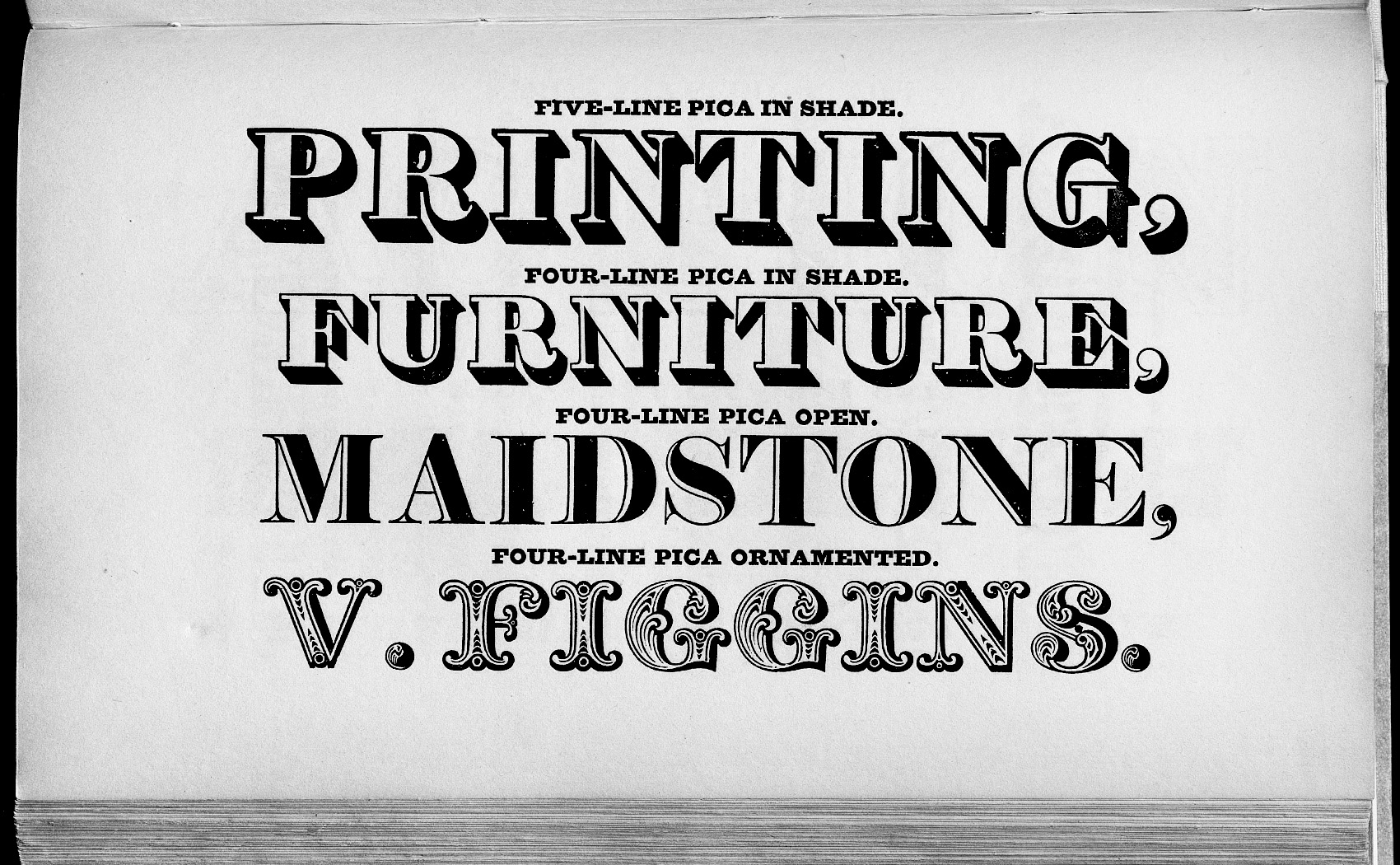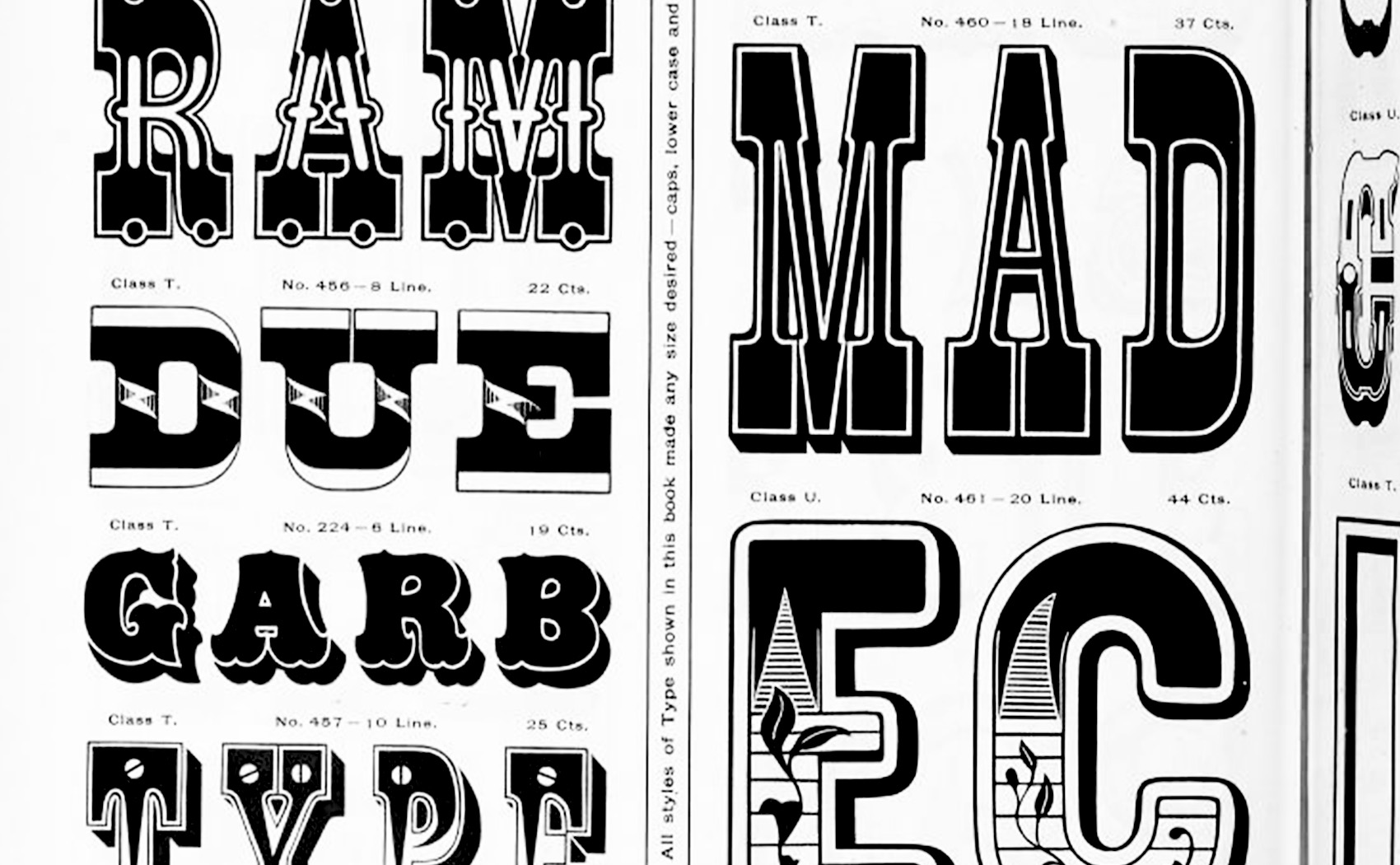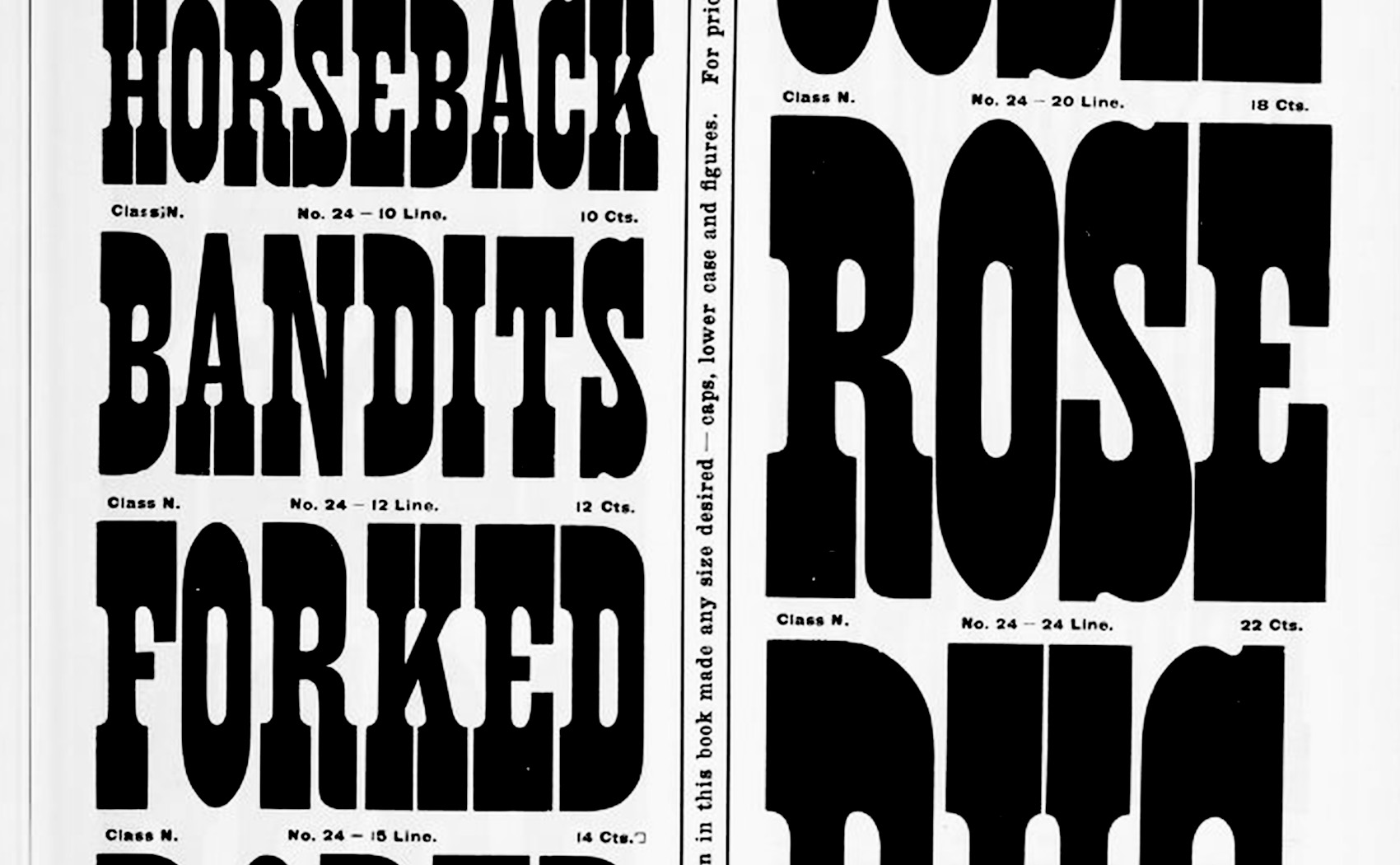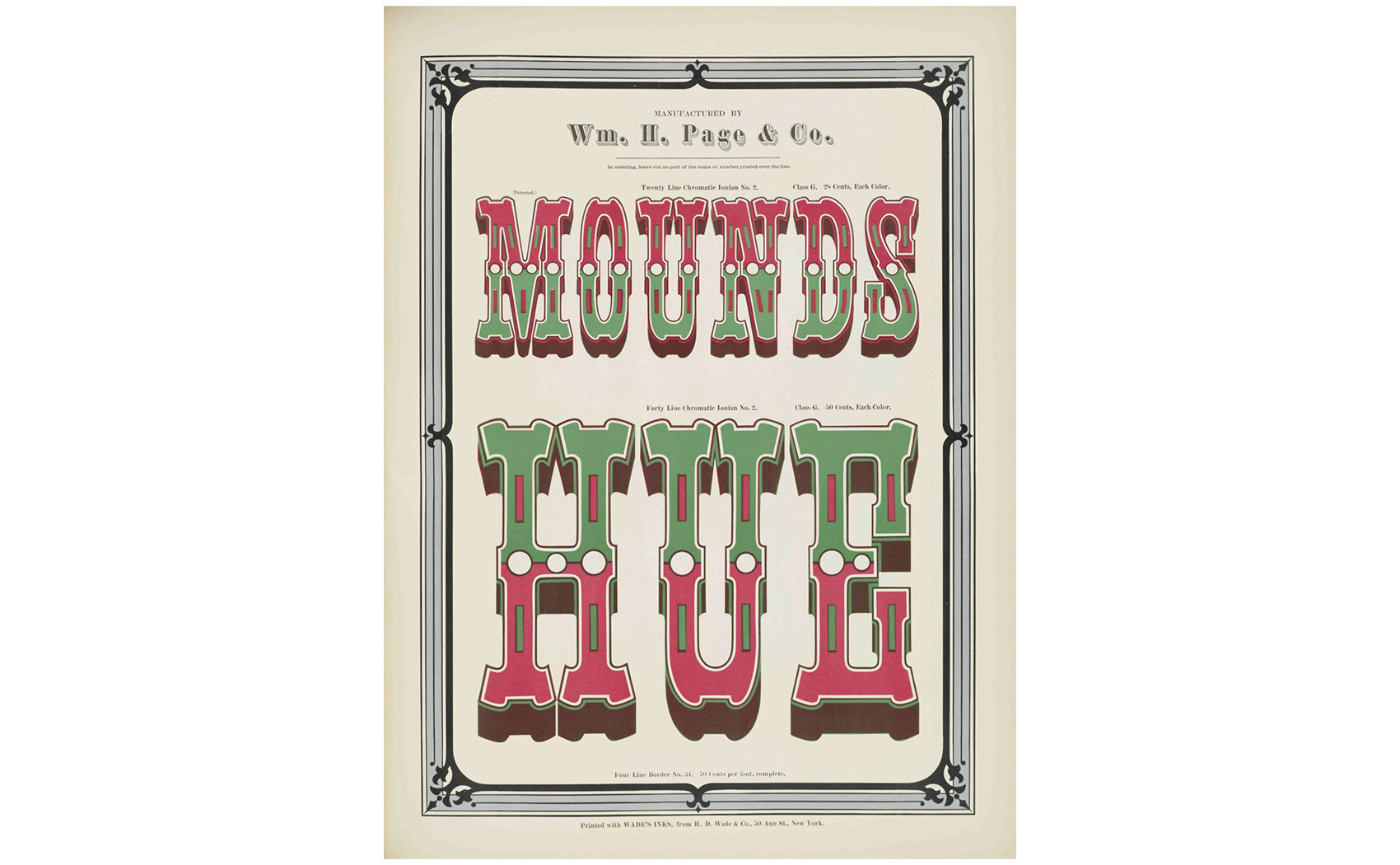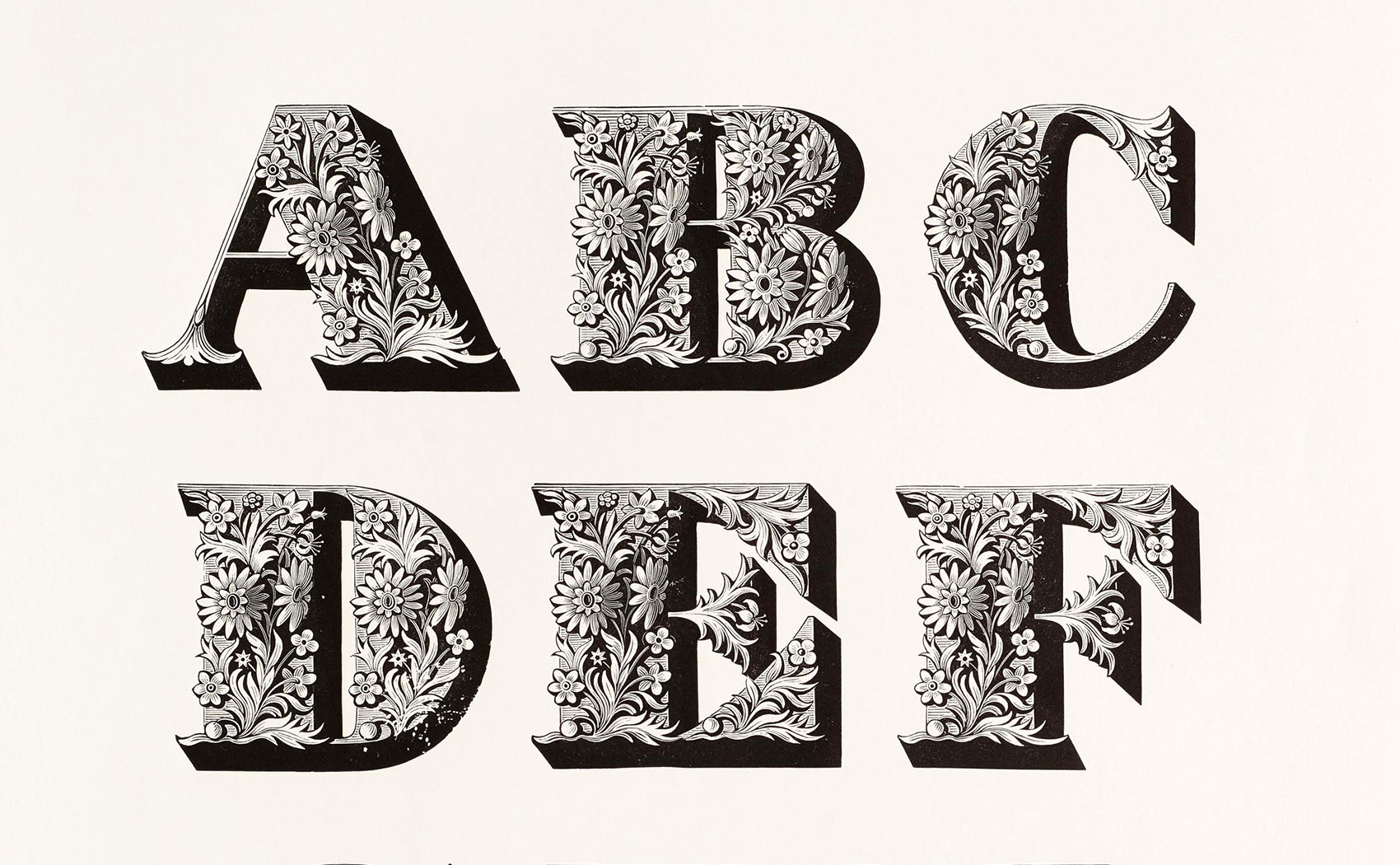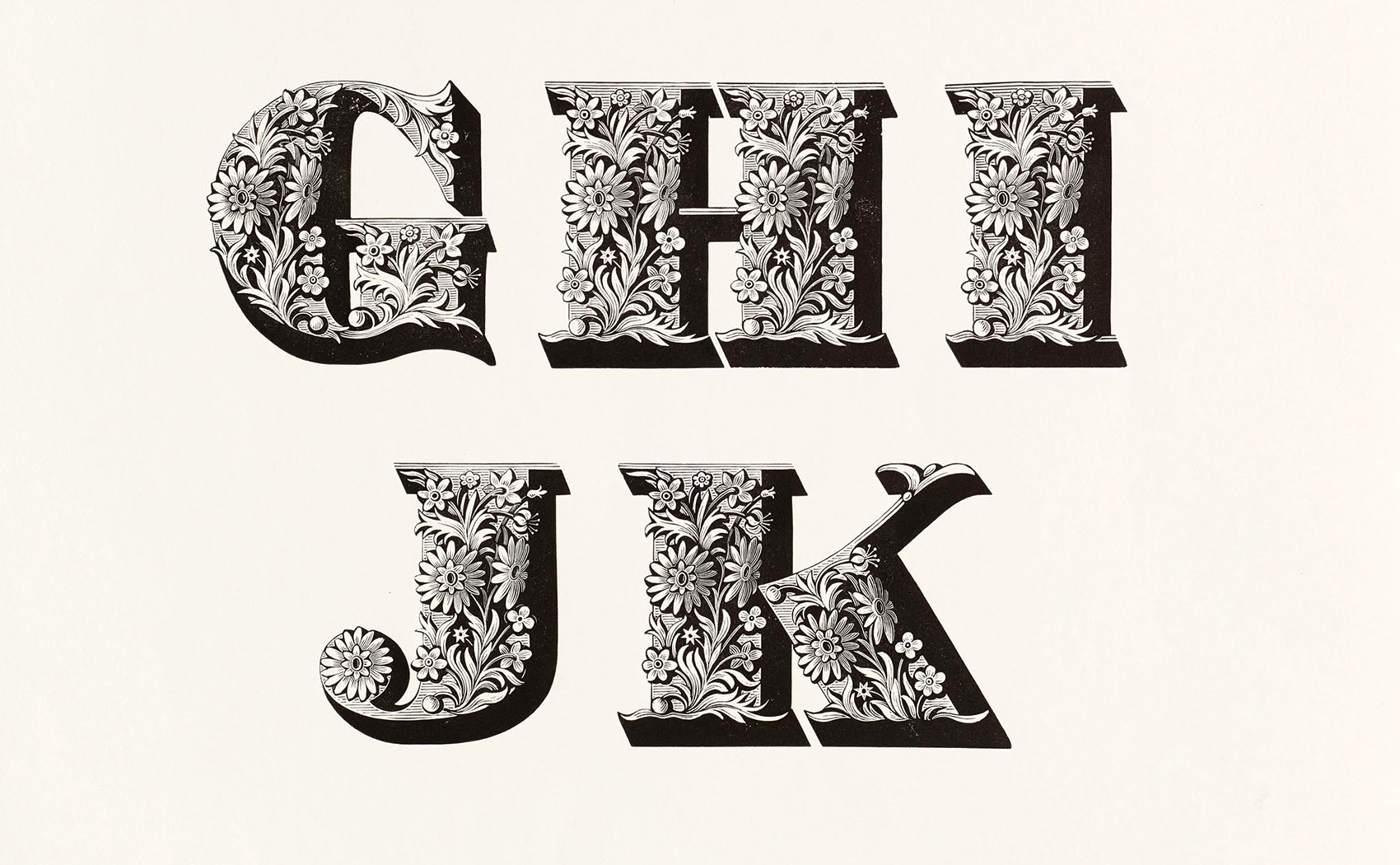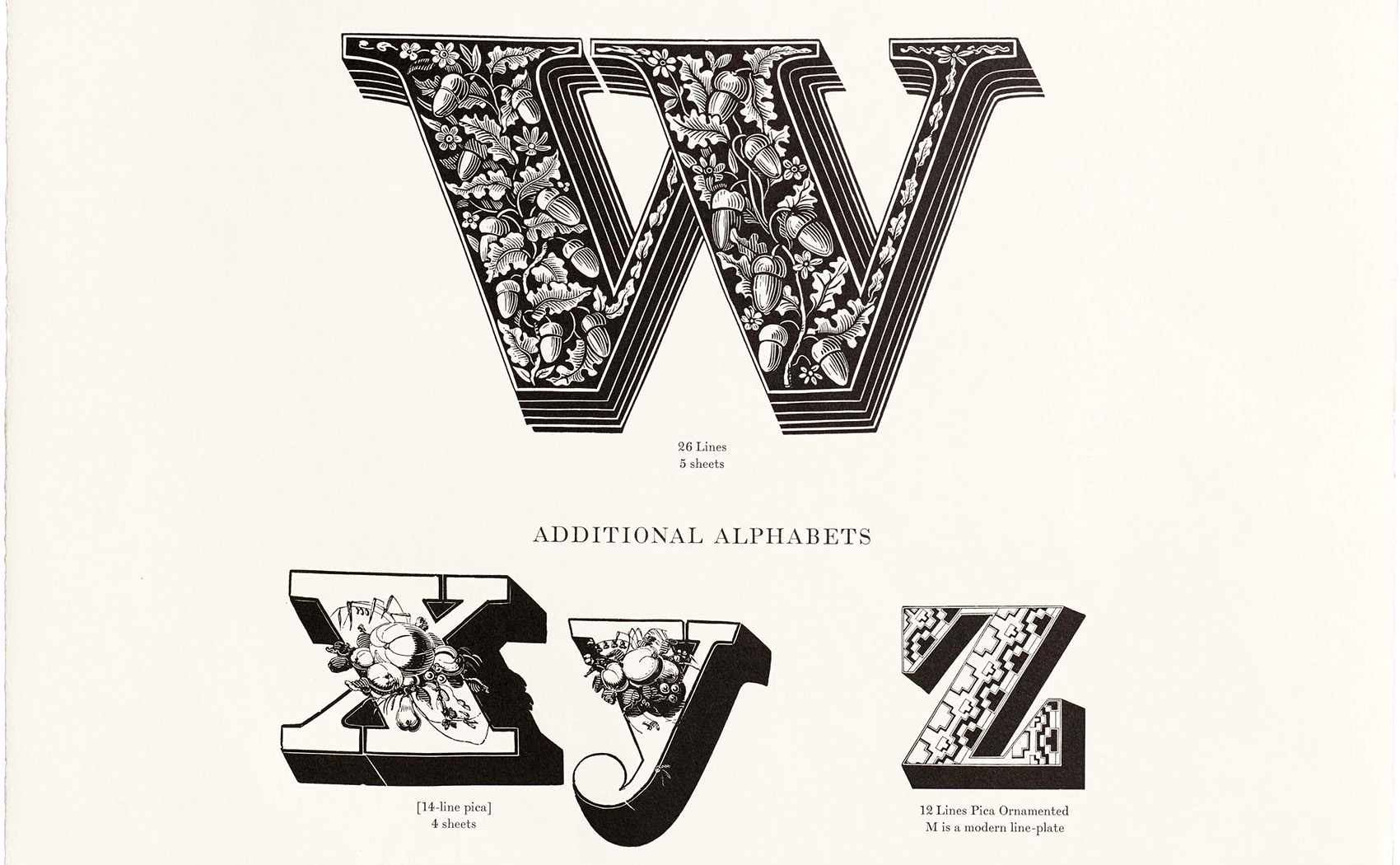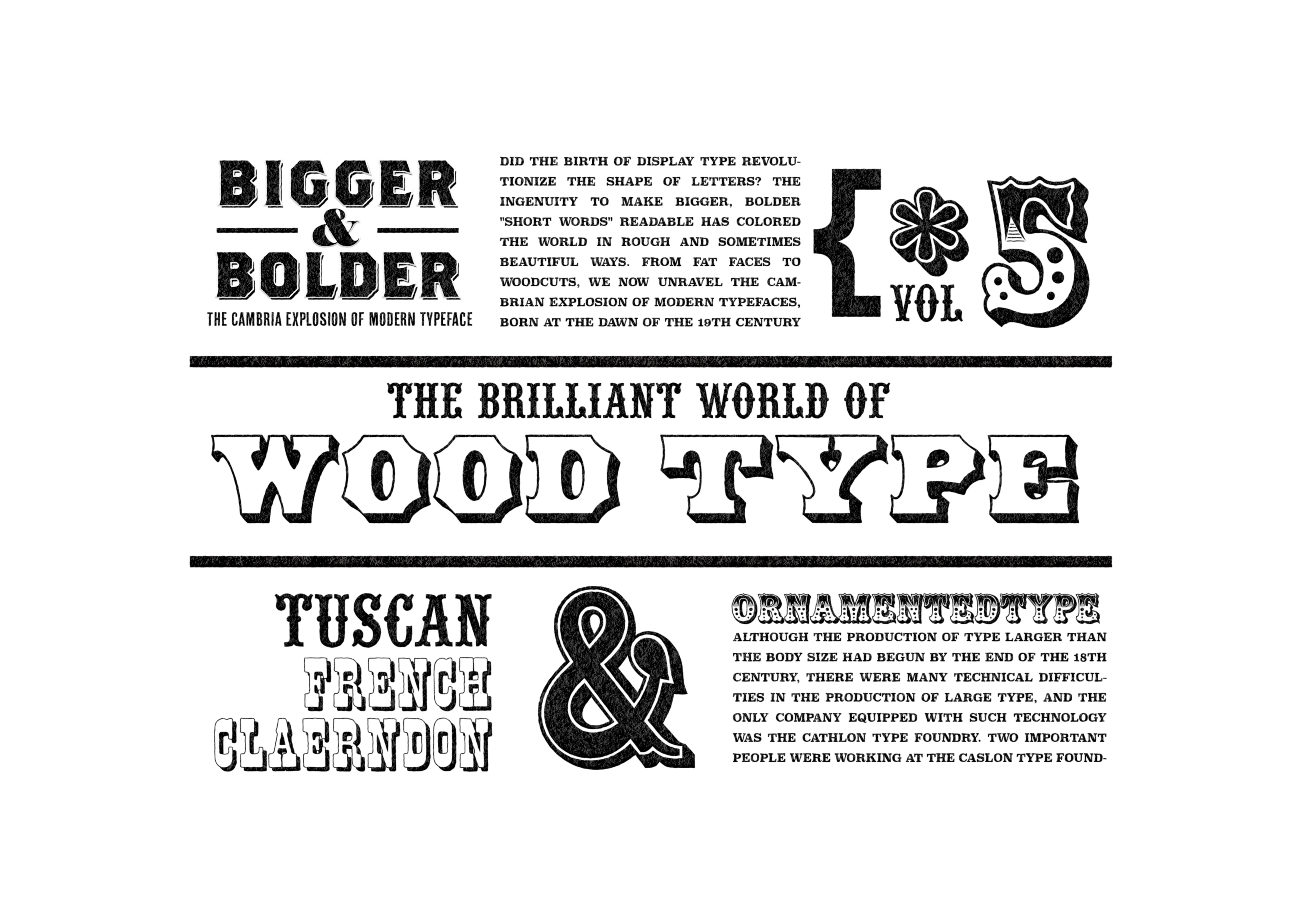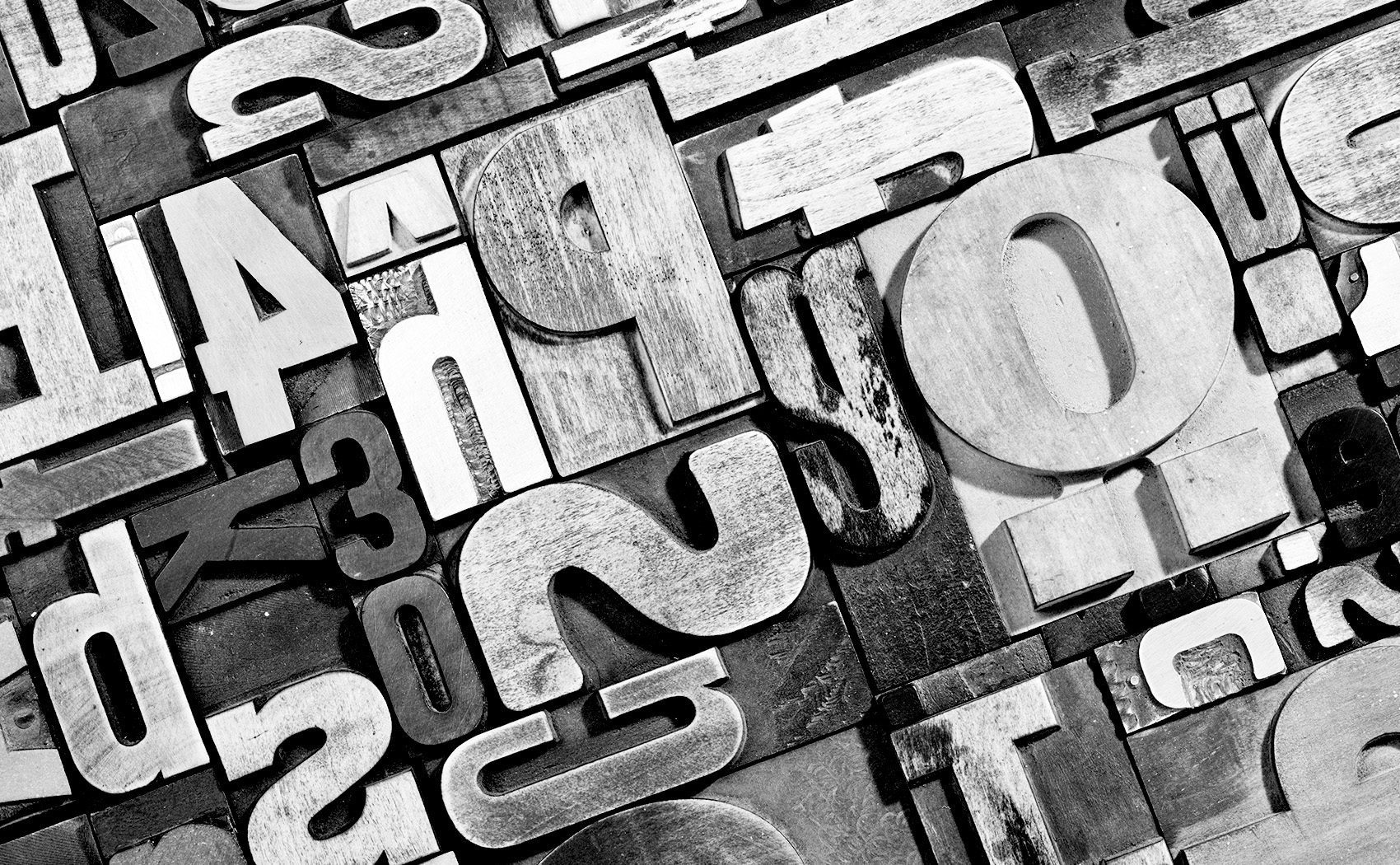
BIGGER & BOLDER
The Cambria Explosion of Modern Typeface
—Vol.05 ウッドタイプの華麗なる世界—
THE BRILLIANT WORLD OF WOODTYPE
ウッドタイプの華麗なる世界
「短い言葉」を読ませるためにディスプレイタイプがより太くより単純化して「黒み」を追求するファットフェイスやスラブセリフの方向性へ進むのと平行して、活字の形にさらに視覚的な要素を追加して文字をいかに「目立たせる」かを追求する「装飾」の可能性を探る方向性が存在していました。 もともと文字を装飾することは、古くは聖書の写本のイニシャルといわれる装飾頭文字のカリグラフィーにおけるテクニックや、近代においてもレタリングやサインペインティングなどで育まれてきた文化があり、それがディスプレイタイプの黎明期に活字に取り入れられることとなりました。おりしも産業革命後のヴィクトリア朝時代は、バロックやロココなどの前時代の貴族的な装飾が、機械化による大量生産技術の開発に伴って安価に行き渡る大衆化がおきていて、デザイン史の中でも装飾の特異点と考えられています。そんな猫も杓子も装飾マシマシなモダンデザイン前夜に起きた、活字の装飾について少しのぞいてみたいと思います。
In parallel with the trend toward fat faces and slab serifs, which pursue “blackness” by making display type thicker and simpler in order to make “short words” readable, there was a trend toward exploring the possibilities of “decoration,” which seeks how to make letters “stand out” by adding more visual elements to the typeface form. Originally, the use of decorative letterforms was a technique in calligraphy, where initials in biblical manuscripts were used to decorate letters, and in modern times, lettering and sign painting have been used to decorate letters. This culture was incorporated into type at the dawn of display type.In the Victorian era after the Industrial Revolution, the aristocratic decorations of the Baroque and Rococo periods were being popularized at low cost with the development of mass production technology through mechanization, and this period is considered a singular point in the history of design. Let us take a look at the decoration of type on the eve of the modern design era, when all the cats and dogs were decorated.
ウッドタイプの誕生The Birth of Wood Type
19世紀までヨーロッパでは活字を作るためには金属鋳造が基本でした。金属活字は一度元となる父型(パンチ)に文字の形を彫刻し、それを母型(マトリクス)に打ち付けて鋳型をつくります。鋳型をつかって鋳造によって複製をしてゆくことで大量に同一の文字を制作することが可能です。それに対して、木製の活字は手作業によって一つづつ複製を強いられるため量産ができず実際的ではないと考えられてきました。時は産業革命の真っ只中、動力を生かした発明に頭をひねる人々がしのぎを削る中、1827年にダリウス・ウェルズが木工機械である「ルータ」を発明したことで状況は一変することになります。ルータは動力を得て木を削ることや磨くことが可能で、この機械化により木製の活字を制作する時間が大幅に短縮し大量生産が可能となりました。そして、1834年に「パントグラフ」が発明されルータとの組み合わせにより手元の作業を正確に拡大複製することが可能となったことで、ウッドブロックをつかった「大きな活字」を制作する条件が整います。ファットフェイスが切り開いたポスター向けのディスプレイタイプの「大きな活字」の需要は右肩上がりに増えているなか、大量生産が可能となった木製の活字は金属活字に対して10分の1程度の価格で提供することが可能でウッドタイプがディスプレイタイプのマーケットへと進出します。さらにダビングやプロトタイピングなど、木製から金属への複製技術の発展もウッドタイプによる装飾などディスプレイタイプのデザインを豊富なものにしてゆきました。
Until the 19th century, metal casting was the basic method of making type in Europe. The metal type was made by engraving the letterforms on a punch, which was then struck into a matrix to make a mold. By using the mold to make reproductions through casting, it is possible to produce identical letters in large quantities. Wooden type, on the other hand, was considered impractical because it could not be mass-produced because it had to be reproduced one by one by hand.In the midst of the Industrial Revolution, when many people were busy trying to come up with new ideas using power, the situation changed when Darius Wells invented the “router,” a woodworking machine, in 1827. The router was powered to sharpen and polish wood, and this mechanization greatly shortened the time required to produce wooden type and enabled mass production. The invention of the “pantograph” in 1834, combined with the router, made it possible to accurately enlarge and reproduce the work at hand, thus creating the conditions for the production of “large type” using wood blocks. The demand for large display type for posters, which Fat Face had pioneered, was steadily increasing, and wood type, which could now be mass-produced at one-tenth the price of metal type, entered the display type market. Wood type entered the display type market. The development of wood-to-metal reproduction techniques, such as dubbing and prototyping, also contributed to the proliferation of display type designs, such as wood type decorations.
ウッドタイプのデザインWoodtype design
産業革命を果たした19世紀のロンドンから、20世紀の中心になる新天地アメリカへと産業や文化が大きく動くとともに、文化の中心をささえる文字もまた求めに応じてカタチを変えてきました。特にウッドタイプの需要が急増した1860年から1890年代のアメリカは西部開拓時代にあたり、開拓の歴史とともにアメリカの文化の根底にウッドタイプが深く刻みこまれてゆくこととなります。ウッドタイプをタイプフェイスデザインの面からみた時、代表的なデザインスタイルには「トスカン」と「フレンチクラレンドン」を挙げることができます。トスカンもクラレンドンもデザイン自体はもともと19世紀のロンドンからやってきました。そう、フィギンズやファンストリートのデザインです。それらが、アメリカで独自の発展を遂げ、いまでは「トスカン・クラレンドン=ウッドタイプ=古き良きアメリカ」のような連想が成立するほど、アメリカ文化と密接なデザインとなっています。ウェスタン映画やベースボールチームに至るまでアメリカ文化には必ずといっていいほどウッドタイプ由来のエレメントが用いられています。
As industry and culture moved from London in the 19th century, the center of the Industrial Revolution, to the United States, the new center of the 20th century, the letters that supported the center of culture also changed form to meet the needs of the times.The 1860s to 1890s, when demand for wood type rapidly increased, was the era of the western frontier, and wood type was deeply engraved in the foundation of American culture as well as the history of the frontier.From the standpoint of type face design, Tuscan and French Clarendon are representative of wood type. Both Tuscan and Clarendon designs themselves originally came from 19th century London. Yes, they are Figgins and Fann Street designs. They have developed in their own way in the United States and are now so closely connected to American culture that the association “Toscan/Clarendon = wood type = good old America” is now established. Elements of the wood type are used in American culture, from western movies to baseball teams.
トスカンTUSCAN
トスカンは特徴的な装飾されたセリフやエレメントを持つものを分類する用語として用いられています。シェイプの特徴では、セリフが二つや三つに枝分かれしたものや、ステムなどの直線部分を絞るような曲線となっていたり、ベースラインとアセンダーラインの中央あたりに装飾的な特徴を持つものをさします。ウッドタイプで好んで用いられたことからウッドタイプと同義的に分類されている場合もあります。ヴィンセント・フィギンズの1801/1815年のカタログに掲載された、FOUR LINE PICA ORNAMENTEDが欧文活字での最初のトスカンであり、ローマンをベースにした文字形で、過度に曲線的で装飾的なセリフと、文字内部へ彫刻のような装飾を施した特徴的なデザインです。
Tuscan is a term used to classify those with distinctive decorated serifs or elements. In terms of shape characteristics, it refers to serifs with two or three branches, curved lines that narrow the stem and other straight parts, and decorative features around the center of the base line and ascender line. Since it is often used in wood types, it is sometimes classified synonymously with wood typesFOUR LINE PICA ORNAMENTED from Vincent Figgins’ 1801/1815 catalog is an early Toscan in European type, a Roman-based letterform with overly curved and decorative serifs and a distinctive design with engraved ornamentation inside the letters. .
アメリカとウッドタイプWood type in US
ウッドタイプはヨーロッパから海を渡った新天地アメリカでさらに独自の発展を遂げてゆくこととります。アメリカ国内で最初にウッドタイプとしてトスカンが登場したのが、Edwin Allen のものが1838年のEdwin Allen 「First Premium Wood types , cut by machinely」に掲載されています。19世紀のアメリカでは機械化した木工によりウッドタイプのファウンダリが成功をおさめ、さまざまなウッドタイプが生まれました。
The wood type was to further develop in its own unique way in the United States, a new country that had crossed the ocean from Europe.The first wood type Tuscan to appear in the U.S. was made by Edwin Allen in 1838 in his “First Premium Wood types , cut by machinely. The success of the wood type foundry led to the creation of a wide variety of wood types.
アンティークトスカンANTIQUE TUSCAN
1850年から1860年にかけてつくられた、スラブセリフを原型に縦線を絞るように曲線でカットしたアンティークトスカンと呼ばれるデザイン。
The design called an antique toscan, was made between 1850 and 1860 and is based on a slab serif, cut with a curved line that narrows the vertical line.
フレンチクレランドンFRENCH CLARENDON
フレンチクラレンドンは、縦線と横線の太さのコントラストが典型的なものとは逆にになったリバースコントラストが特徴のデザイン。同時代にはリーバースコントラストのイタリアンと呼ばれるタイプデザインがあり、スラブセリフなどとともに太いセリフに特徴を持たせることでユニークさを強調している。19世紀のアメリカで好んで用いられたことで、現代でも西部開拓時代を演出する際に、指名手配のビラのWANTEDや、西部劇やテーマパークなどの看板などでしばしばつかわれています。
French Clarendon is a design characterized by reverse contrast, in which the contrast between the thickness of the vertical and horizontal lines is reversed from the typical one. The type design of the same period, called Italian with leavers contrast, emphasizes the uniqueness of the thick serifs by making them distinctive, along with slab serifs, etc. A favorite in 19th century America, it is still used today in Westerns, such as WANTED on wanted flyers, and on signs in Westerns and theme parks.
ウッドタイプの装飾Wood Type Decoration
文字自体のフォームのデザインよりも、装飾性という部分でウッドタイプは鋳造活字では不可能だった細やかな装飾を可能にしました。加工の容易な木版はイラストレーションに向いており、もともと凸版印刷において、金属活字と木版のイラストレーションという組み合わせで行われていたものが、ウッドタイプの登場で、文字にイラストレーティブな装飾を施したものや木版画の手法を持ち込んだ表現が数多く登場しました。その中でも装飾の完成度の高かった、ルイ・ジョン・プーシェ Louis John Pouchée のアルファベットと、多色印刷が可能なWilliam Hamilton Pageのクロマティックウッドタイプを紹介します。
More than the design of the form of the letter itself, wood type enables detailed decoration that was not possible with cast type. Woodblock, which is easy to process, is suitable for illustration. Originally, the combination of metal type and woodblock illustration was used in letterpress printing, but with the advent of woodtype, many illustrative decorations were added to the letters and woodcut techniques were brought into the process. The wood type was a combination of type and woodblock illustration.This section introduces Louis John Pouchée’s alphabets, which were highly decorated, and William Hamilton Page’s chromatic wood types, which could be printed in multiple colors.
W・HページのクロマティックWillam Hamilton Page
19世紀のアメリカでウッドタイプのデザインの主要人物でクロマティックウッドタイプを開発して大成功しました。クロマティティックタイプとは多色刷りを可能にするウッドタイプで、重ね刷りするために色数にセパレートしたデザインをもつ活字です。
Willam Hamilton Page was a major figure in 19th-century American wood type design and a highly successful developer of chromatic wood type. Chromatic type is a wood type that allows multi-color printing and has a design that separates the number of colors for overprinting.
ルイ・ジョン・プーシェの装飾Louis John Pouchée
もっとも美しいとされているウッドタイプとして名高いルイ・ジョン・プーシェ Louis John Pouchée のアルファベット。1820年代に手彫りされた活字としてはもっとも豪華な装飾が施されたものです。レターフォームはソーンのファットフェイスをベースにしていますが、技巧に富んだ豪華な装飾が施されており目を見張るものがあります。写真はロンドンのセント・ブライド・プリンティング・ライブラリー所蔵のもの。
Louis John Pouchée alphabet, considered one of the most beautiful wood types, is the most ornately decorated hand-engraved type of the 1820s. The letterforms are based on the Thorne fat face, but are spectacularly decorated with skillful and lavish ornamentation. The photograph is from the collection of the St. Bride’s Printing Library, London.
ウッドタイプの現在Woodtype today
現在では、活版印刷と同様に大規模に使われることは無くなりましたが、独自のカスレによる温かみや豊富な装飾は近年の再評価も入り今も人々を惹きつけています。木製で相当数が製作されていたため現存しているものも多く、アメリカ国内ではアンティークのインテリア雑貨などを扱う店で見かけることもあります。さまざまなフォントがデジタイズされており、ウッドタイプのタイプフェイスデザインをデジタルフォントで利用することができます。とくに2012年に設立されたHWT(Hamilton WoodType Collection )ではウッドタイプの特徴的でクラシックなものが数多くリバイバル・デジタイズされています。
Today, as with letterpress, it is no longer used on a large scale, but the warmth of its unique cusps and abundant decoration have been reevaluated in recent years and still attract people today. Many of them are still in existence, and can be found in antique stores selling interior goods in the United States.Various fonts have been digitized, and wood typeface designs can be used in digital fonts. In particular, the Hamilton WoodType Collection (HWT), established in 2012, has revived and digitized many characteristic and classic wood type designs.
デジタルフォント
-
Rosewood
1874年のウィリアム・ペイジのクロマティックウッドタイプをモデルに作られた
Modeled after William Page’s chromatic wood type of 1874
Zebrawood
1854年のウェルズ・アンド・ウェッブ活字会社の見本カタログを元にしたアンティークトスカン
Antique Tuscan based on an 1854 Wells and Webb Type Company sample catalog
HWT AMERICAN
1874年のウィリアム・ペイジのクロマティックウッドタイプをモデルに作られた
Modeled after William Page’s chromatic wood type of 1874
French Clarendon
ウィリアム・ペイジのウッドタイプをもとにしたフレンチクレランドン
French Clelandon based on William Page’s wood type.